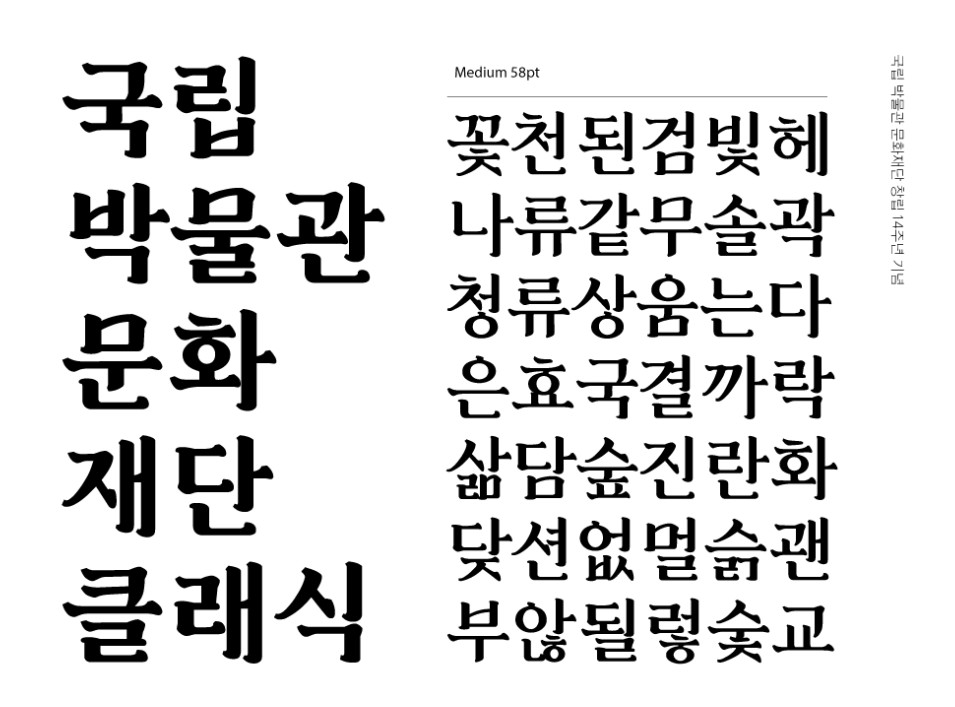
국립박물관문화재단클래식 — 국립박물관문화재단에서 배포하는 무료 폰트입니다. 고전적인 세리프 구조에 굵고 날카로운 획을 더한 장식적인 명조체
국립박물관문화재단이 창립 14주년을 기념해 배포한 서체입니다. 흔히 국립중앙박물관문화재단으로 불리지만 정확한 기관명은 국립박물관문화재단입니다.
재단이 쓴 조형 설명은 없어 형태는 파일을 보고 적습니다. 부리가 있는 계열이고 받침 유무에 따른 높이 차가 거의 없는 네모틀이며 낱자는 정사각형에 가깝습니다. 자면을 적당히 채워 전시 도록이나 문화 콘텐츠에 얹었을 때 격식이 살아납니다.
굵기는 Light와 Medium, Bold 세 가지이고 현대 한글 11,172자를 모두 담았습니다. 굵기가 셋이라 제목과 본문을 한 벌로 처리할 수 있습니다.